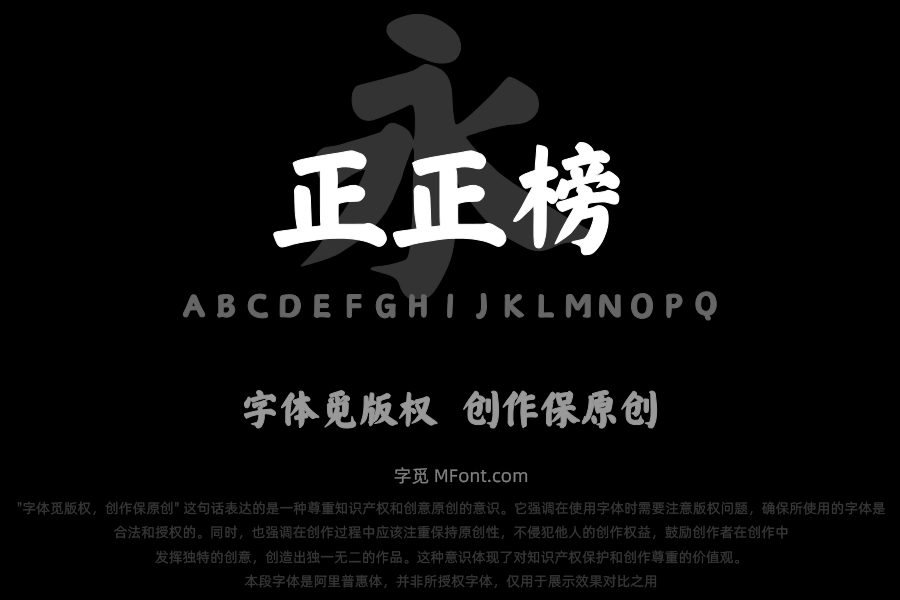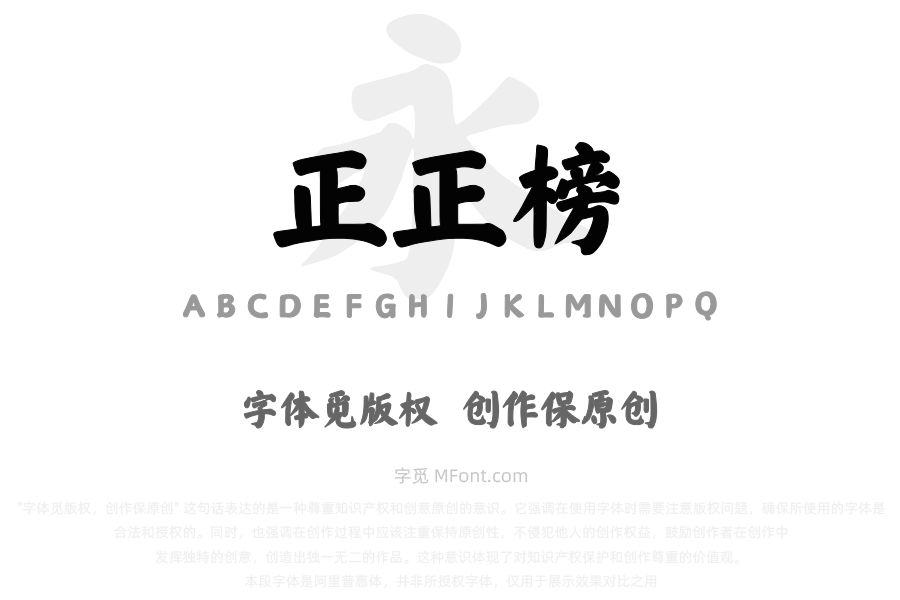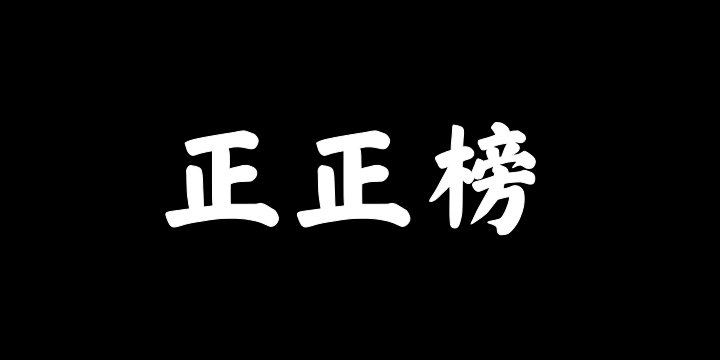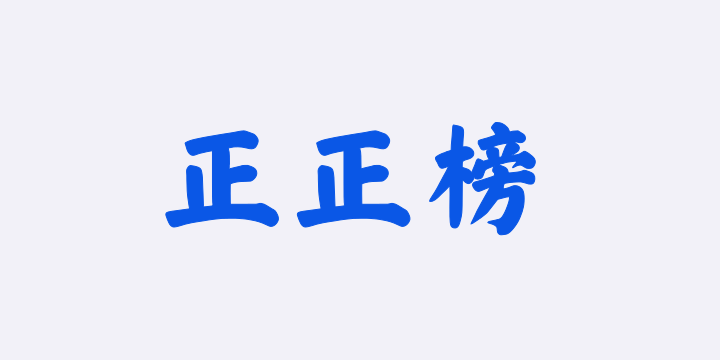
字潮正正榜
关于字潮正正榜字体字库信息
字体全名: 字潮正正榜
铸字厂: 字潮字库
设计师: 丁道华
字体简介: 字潮正正榜汲取榜书艺术之精髓,融其大气磅礴、雄浑厚重之格调,成就字形之刚健恢弘。其笔画粗壮有力,如铁画银钩,极具视觉张力与冲击力,字形更为开阔舒展,结构严谨而不失灵动,疏密有致,张弛有度。